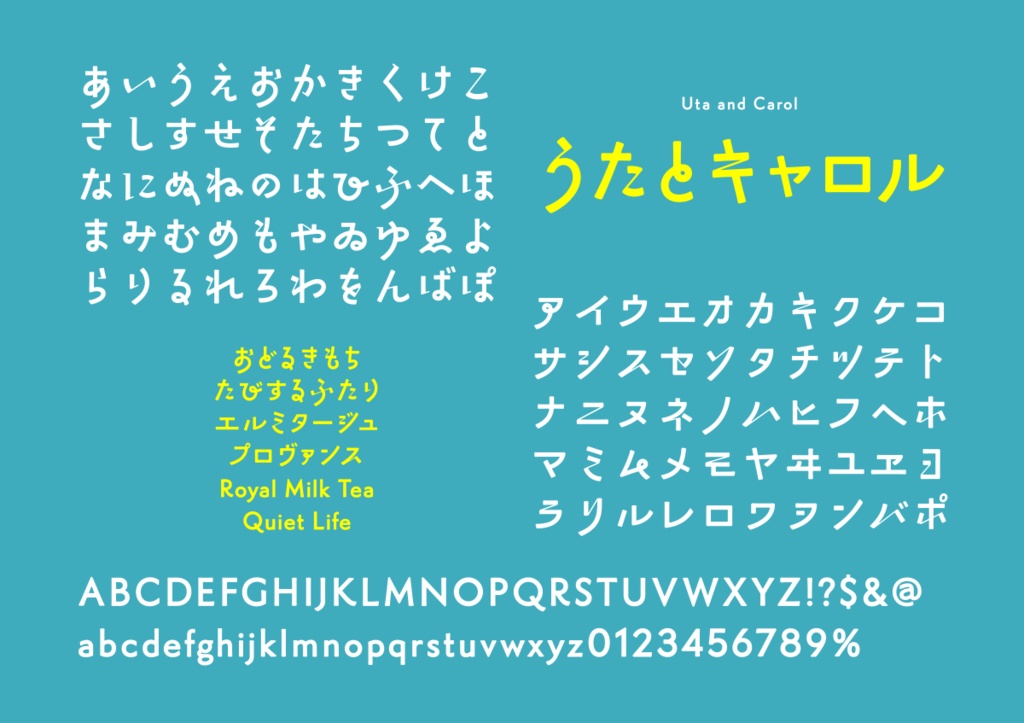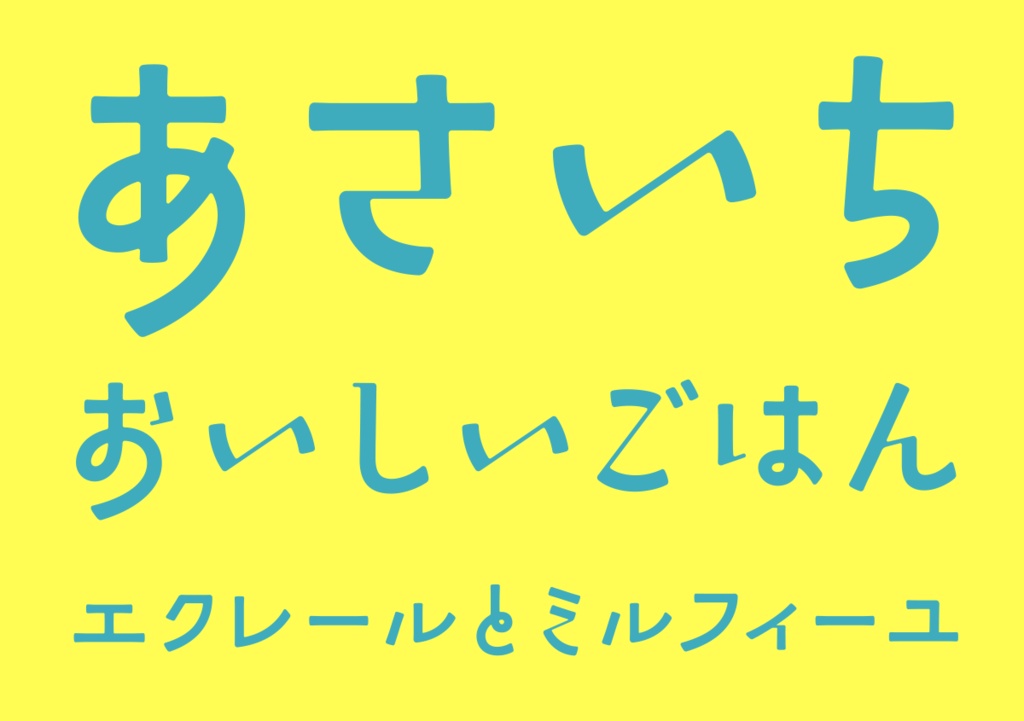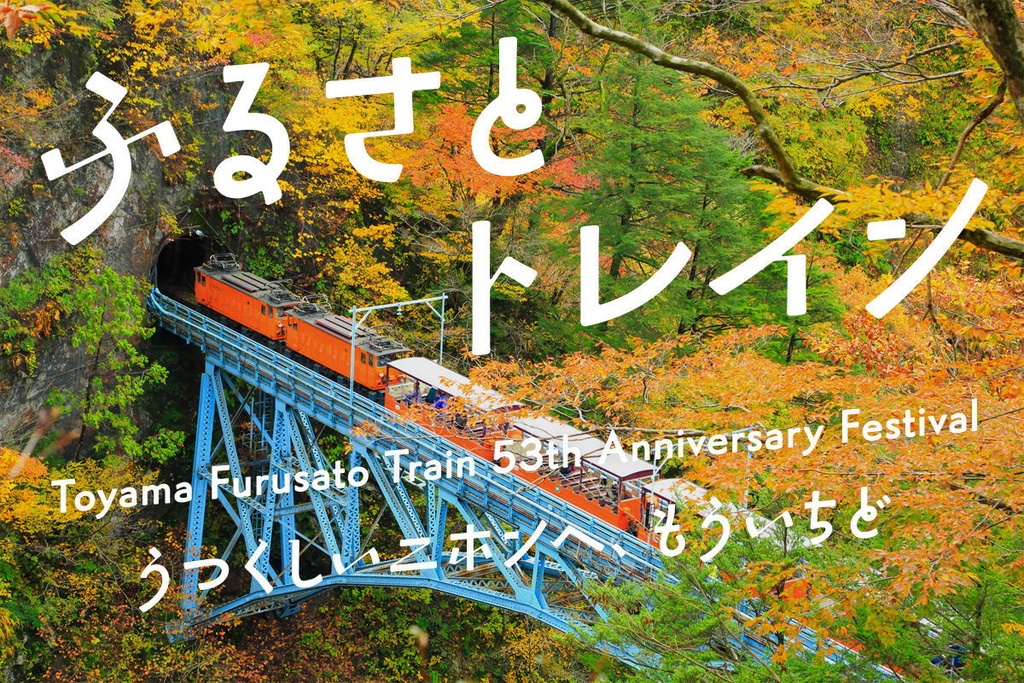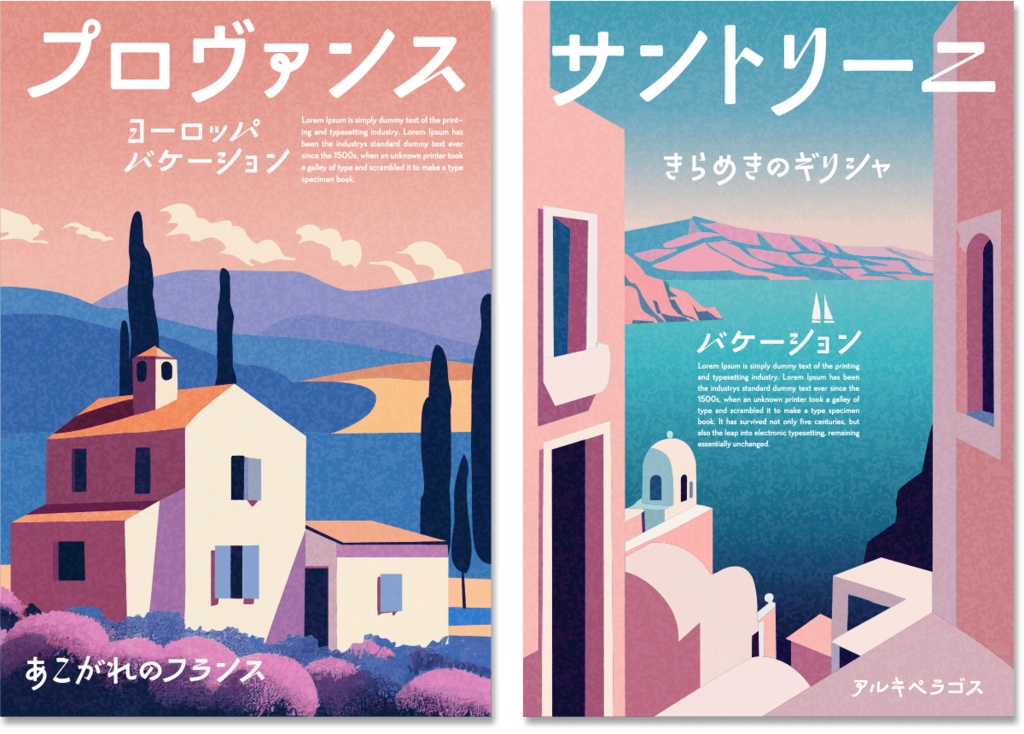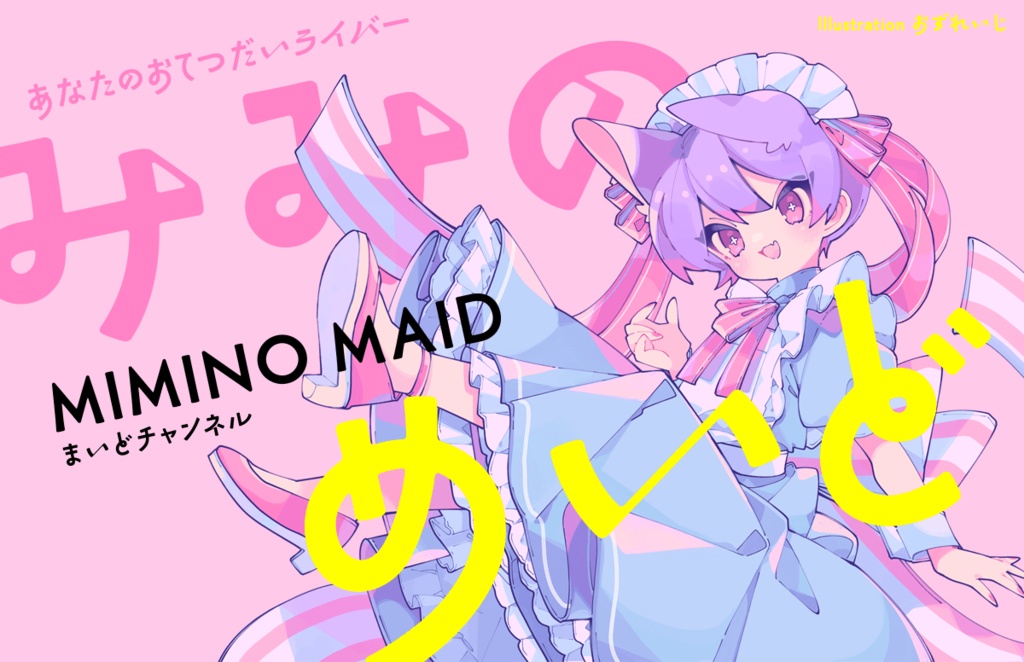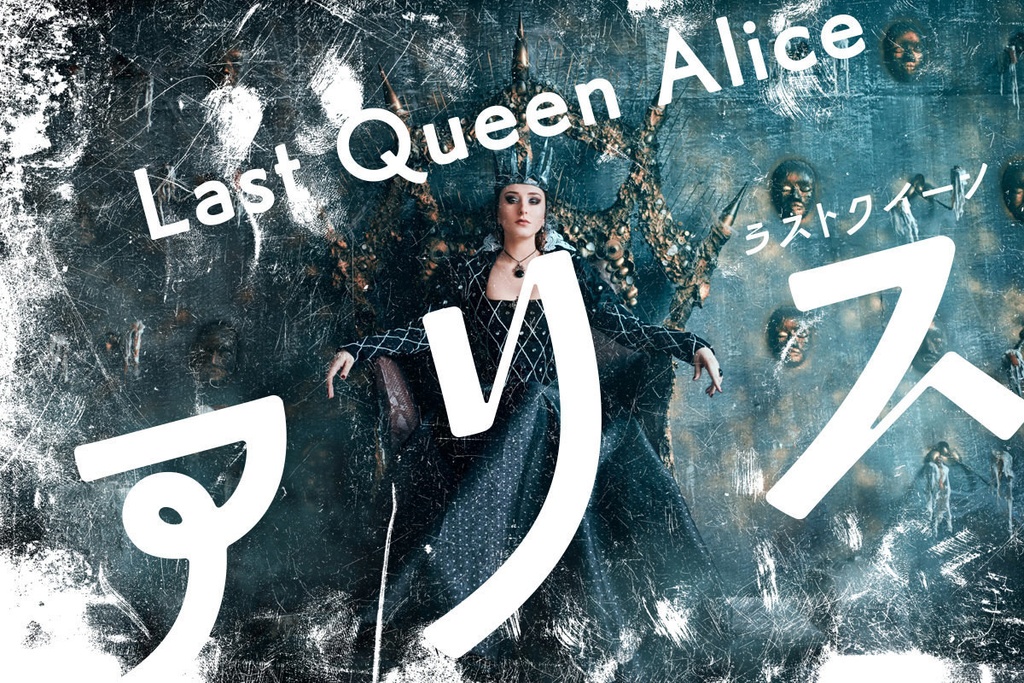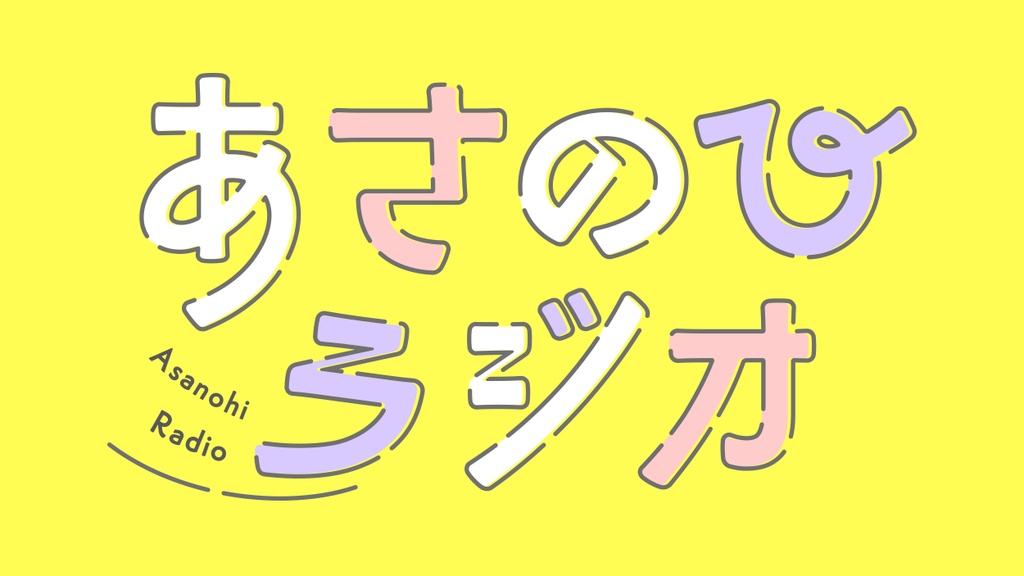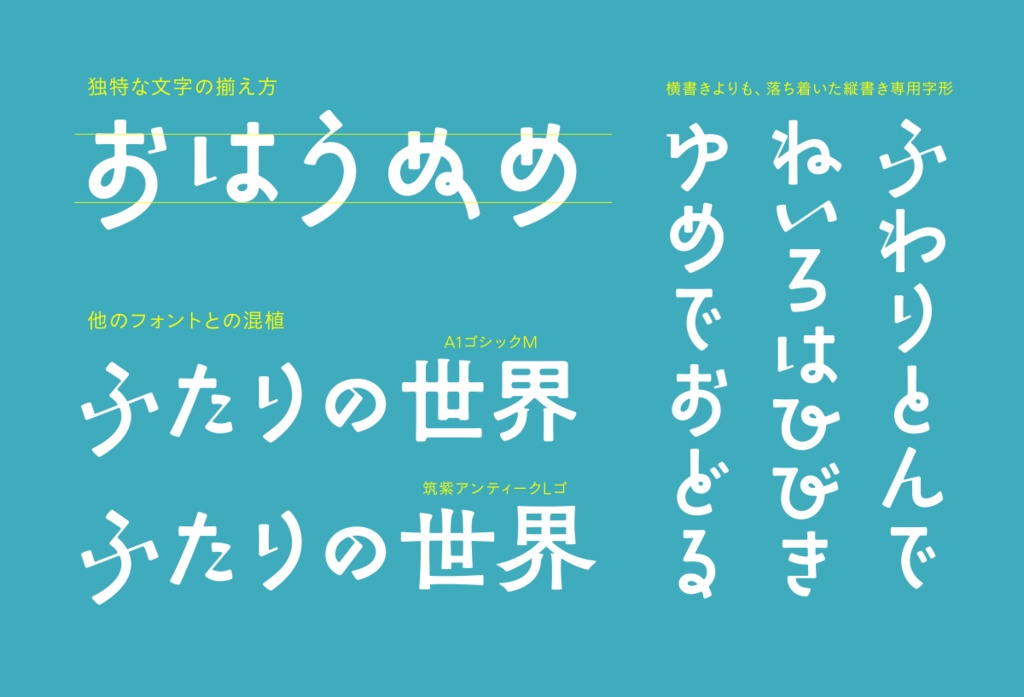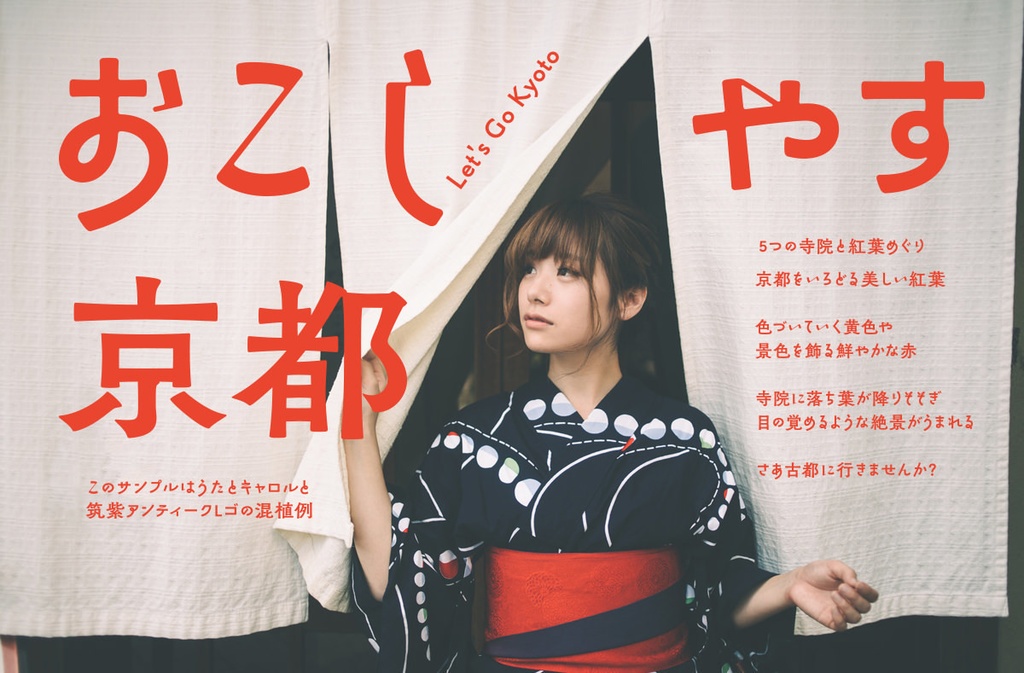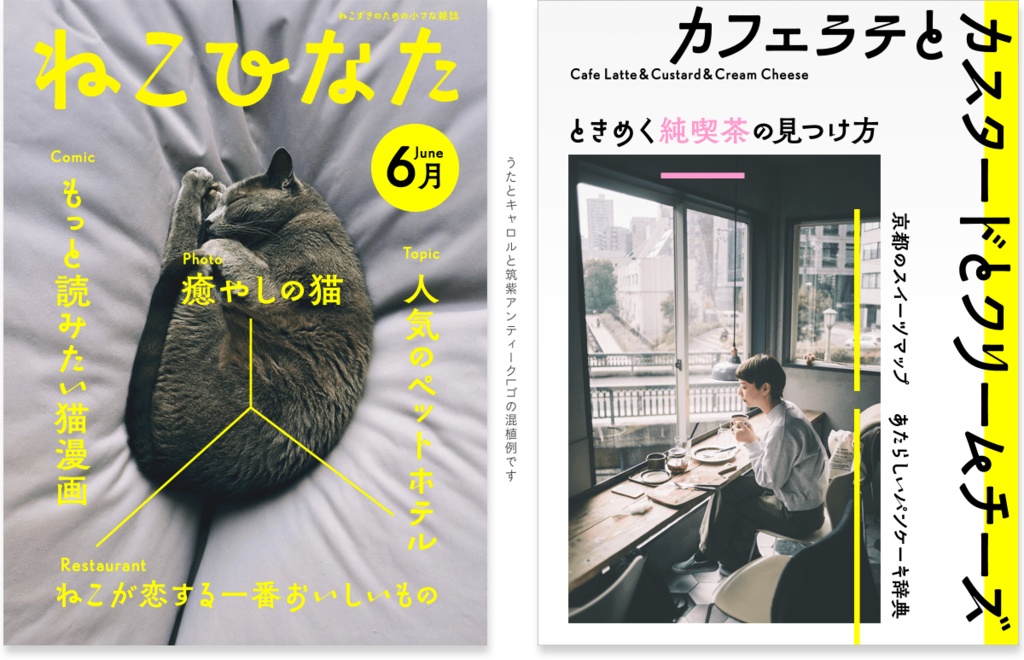
うたとキャロル フォント
下側に流れるような自由なラインの角ゴシック体。遊び心のあるデザインは、使うだけで楽しい世界観が生まれます。モダンさとレトロさのブレンドが絶妙で、幅広い用途に利用できるのも嬉しいポイント。ロゴデザイン、動画サイトへの文字入れ、書籍への使用などで大活躍です。 ■動作環境 Mac:システム/OS X対応(10.x)〜最新のOS X Windows:OS/日本語版Windows2000、XP、VISTA、Windows7〜11以降 フォント形式:OpenTypeフォント 1商品(1ライセンス)につき1ユーザー1PCのみがご利用いただけます。複数人で使用する場合は人数分をご購入ください。 ■収録文字について 収録文字数770字。※収録文字はアルファベット、ひらがな、カタカナ、約物の一部。 ■安心して使えるロイヤリティフリーの書体 あらゆる商用・デザイン用途(印刷物・ゲーム・アプリ・映像・動画・ロゴ・同人作品)に使用できる、商用申請の必要のないロイヤリティフリーの書体になります。文字の加工・変形も可能です。ご安心ください。 ■OpenType機能 詰め組み機能 ペアカーニング(仮名・プロポーショナル欧文) 字形切り替え機能(1つの文字で異なる字形を用意しています)